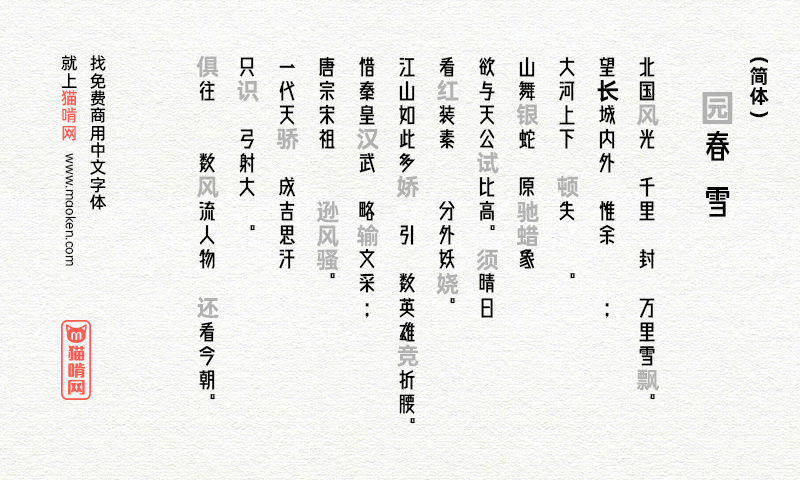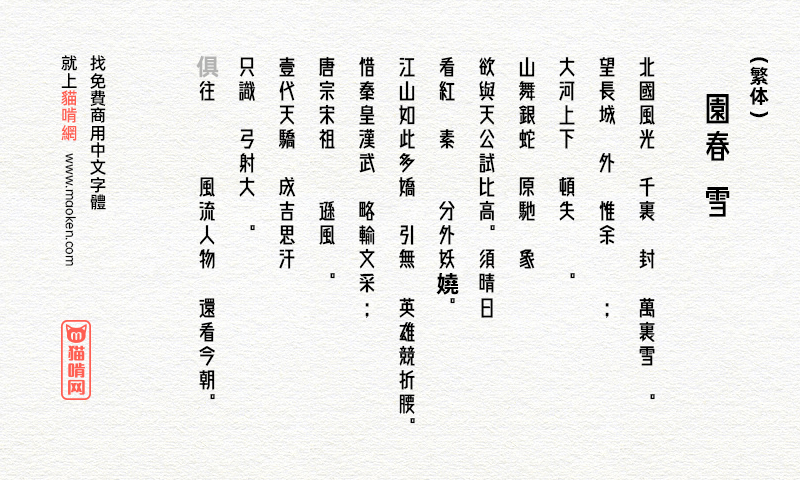
廻想体:来自中二记忆中的理想字体
「廻想体」是由日本もじワク研究网站发布于2018年4月27日。 「廻想体」 文字给人一种秀丽纵长的印象,虽然是日本字体,但是由于日本与我们中国渊源颇深,所以这套字体中也包括不少的常用汉字。 可能会缺少某个几个字符,毕竟日本的汉字使用跟中国的汉字还是有点不同的 ,但在可免费商用的字体极度缺乏的时代,使用这些字体还是不错解决方案。